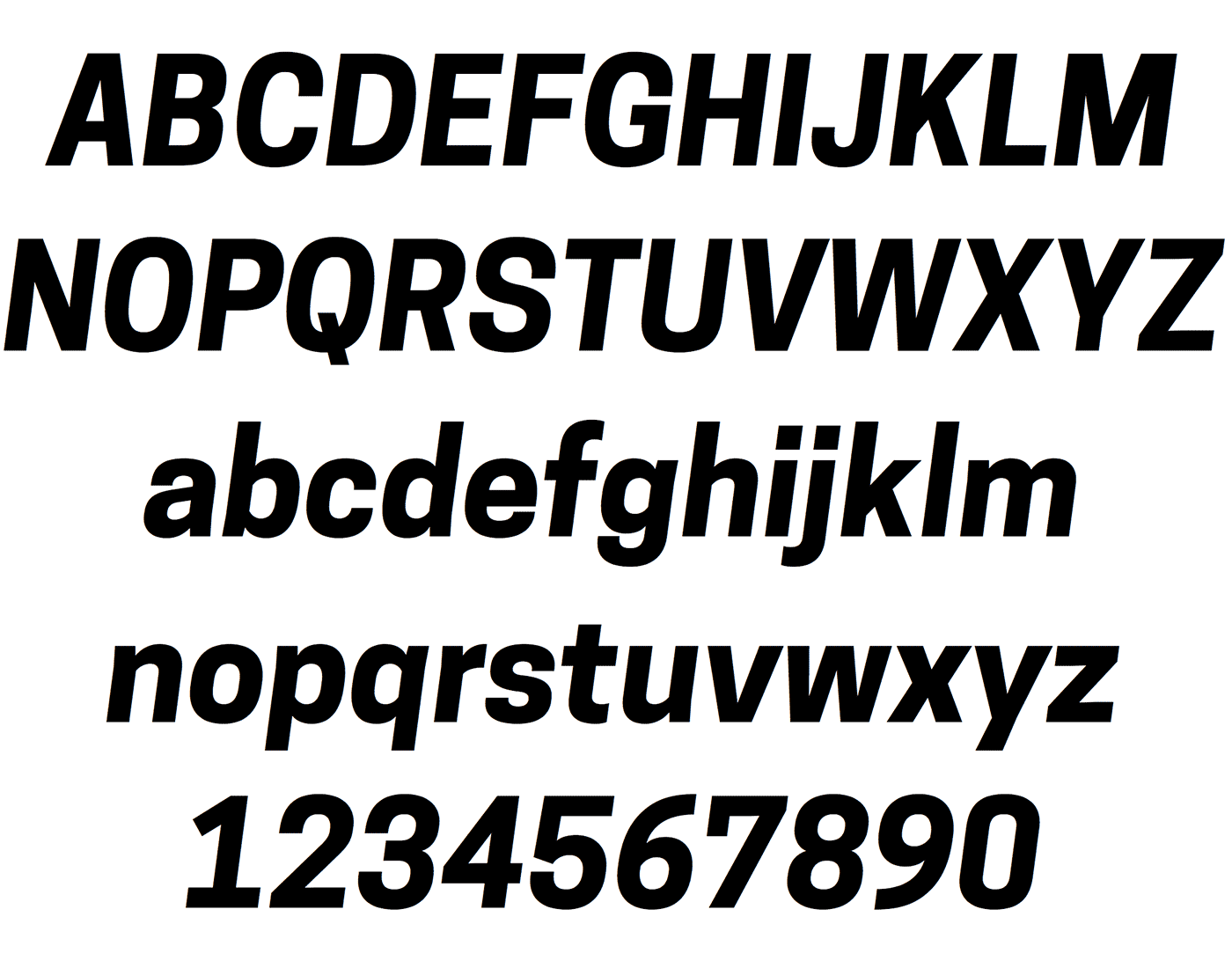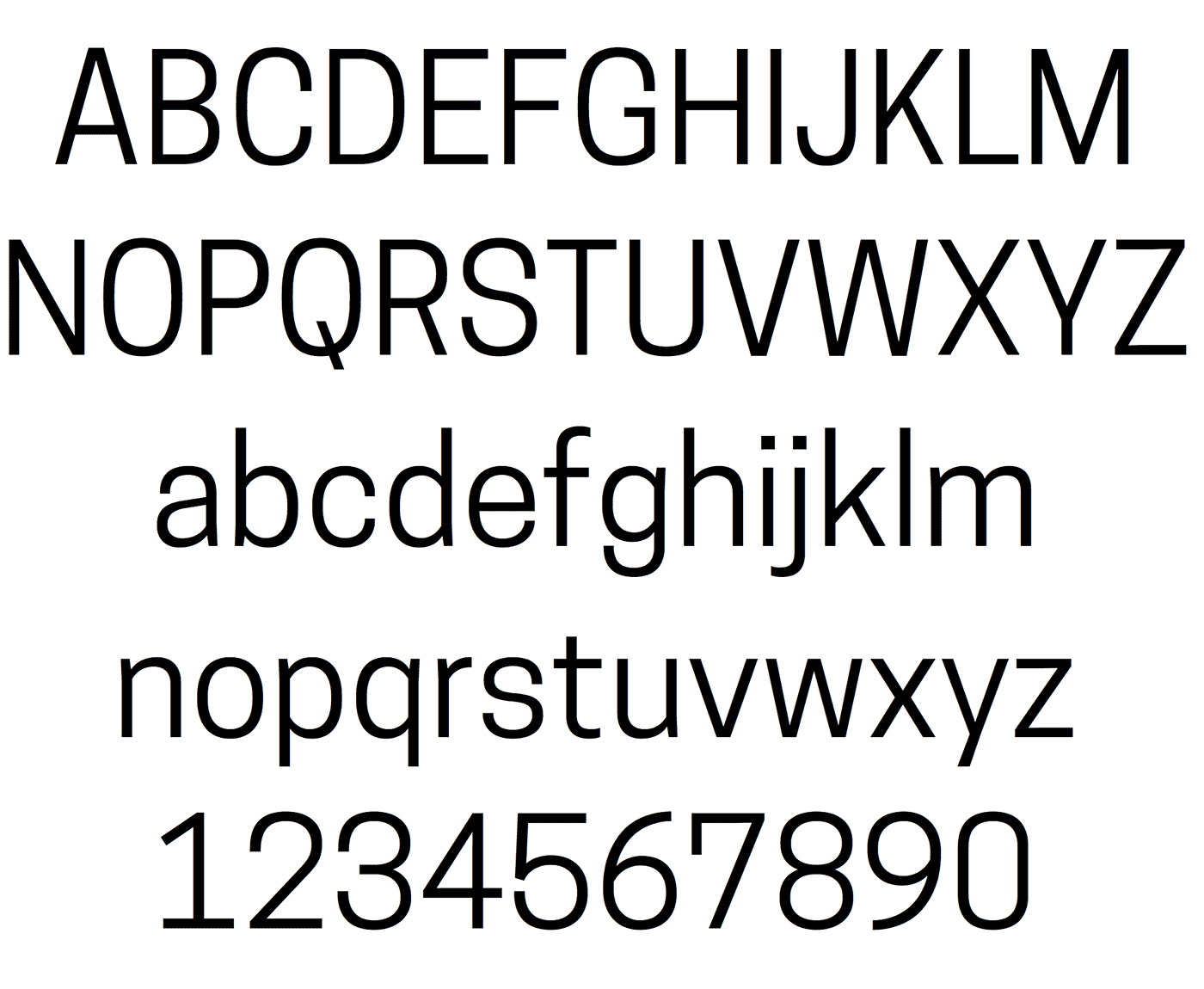
Cooper Hewitt 1.0
Die Schrift entstand ursprünglich für das gleichnamige Museum Cooper Hewitt in New York. Dennoch steht die statische Groteskschrift unter Open Font License und kann somit auf vielfältige Weise eingesetzt werden. Es stehen sieben Strichstärken mit Kursiven zur Verfügung.
Chester Jenkins